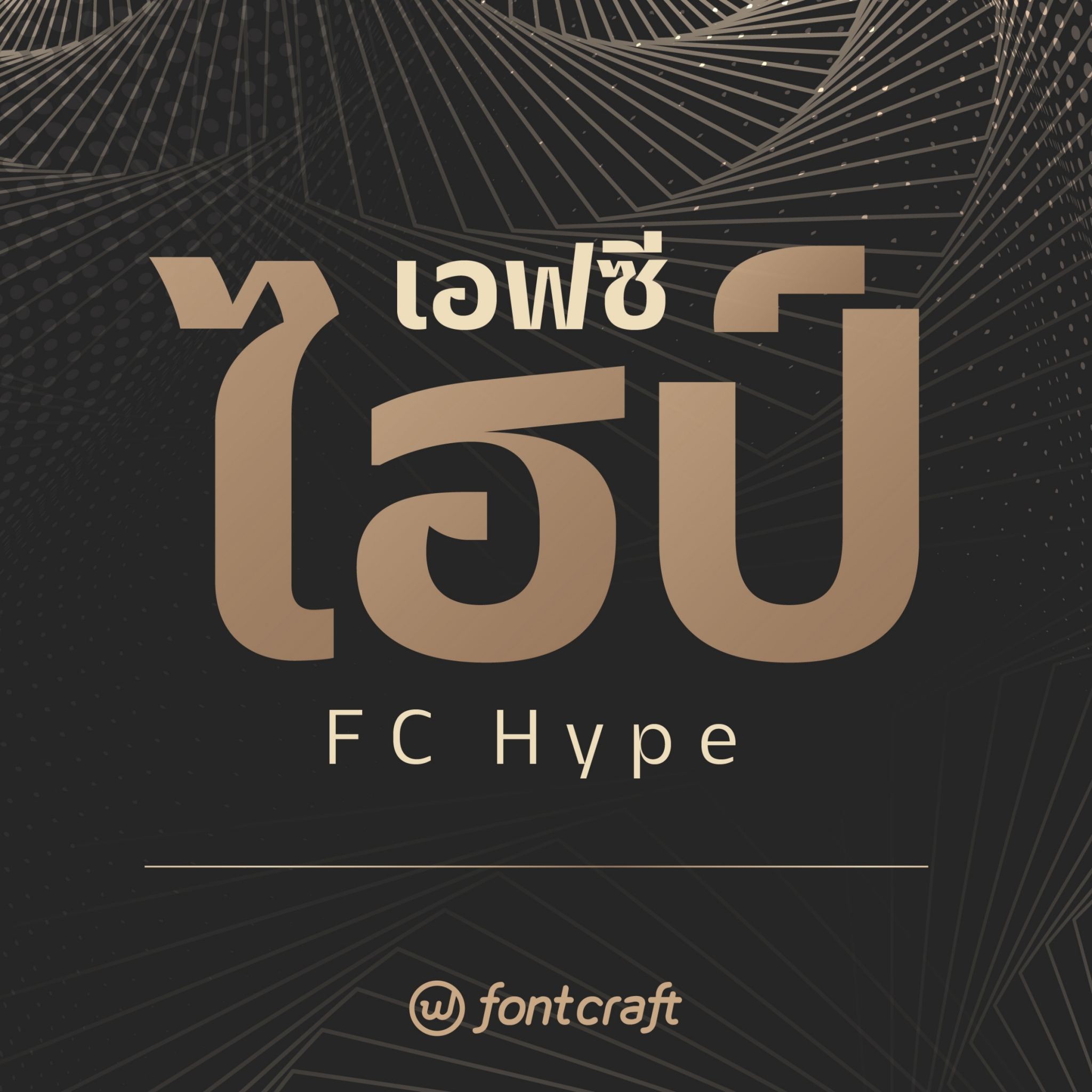
เอฟซี ไฮป์ (FC Hype)
ฟอนต์เอฟซี ไฮป์ (FC Hype)
Are you looking closely?
แบบฟอนต์ Contrast จัด รวมกับโครงสร้างสลับซับซ้อน เย้ายวนชวนคุณให้เข้ามาดูใกล้ๆ
ฟอนต์สไตล์กึ่งทางการไร้หัว ที่อัดแน่นด้วยจุดคอดแคบ เกิดเป็น Contrast อันเป็นเอกลักษณ์
สามารถใช้กับงานแนว Luxury ไปจนถึง Hipster ที่มองหาความแตกต่าง
Memo เล็กๆ น้อยๆ สำหรับฟอนต์ตัวนี้ครับ
- ฟอนต์นี้ใช้ระบบ Mark โดยเพิ่มแนวคิดส่วนตัวเข้าไปว่า หากผู้ใช้หรือโปรแกรมที่ใช้ไม่สามารถเรียกใช้ Mark ได้ ให้กำหนด Default วรรณยุกต์ลอยก่อน (ปกติระบบ Mark มักเจอปัญหาวรรณยุกต์จม) เพื่อให้พออ่านได้ ดีกว่าอ่านไม่ออกเลยครับ